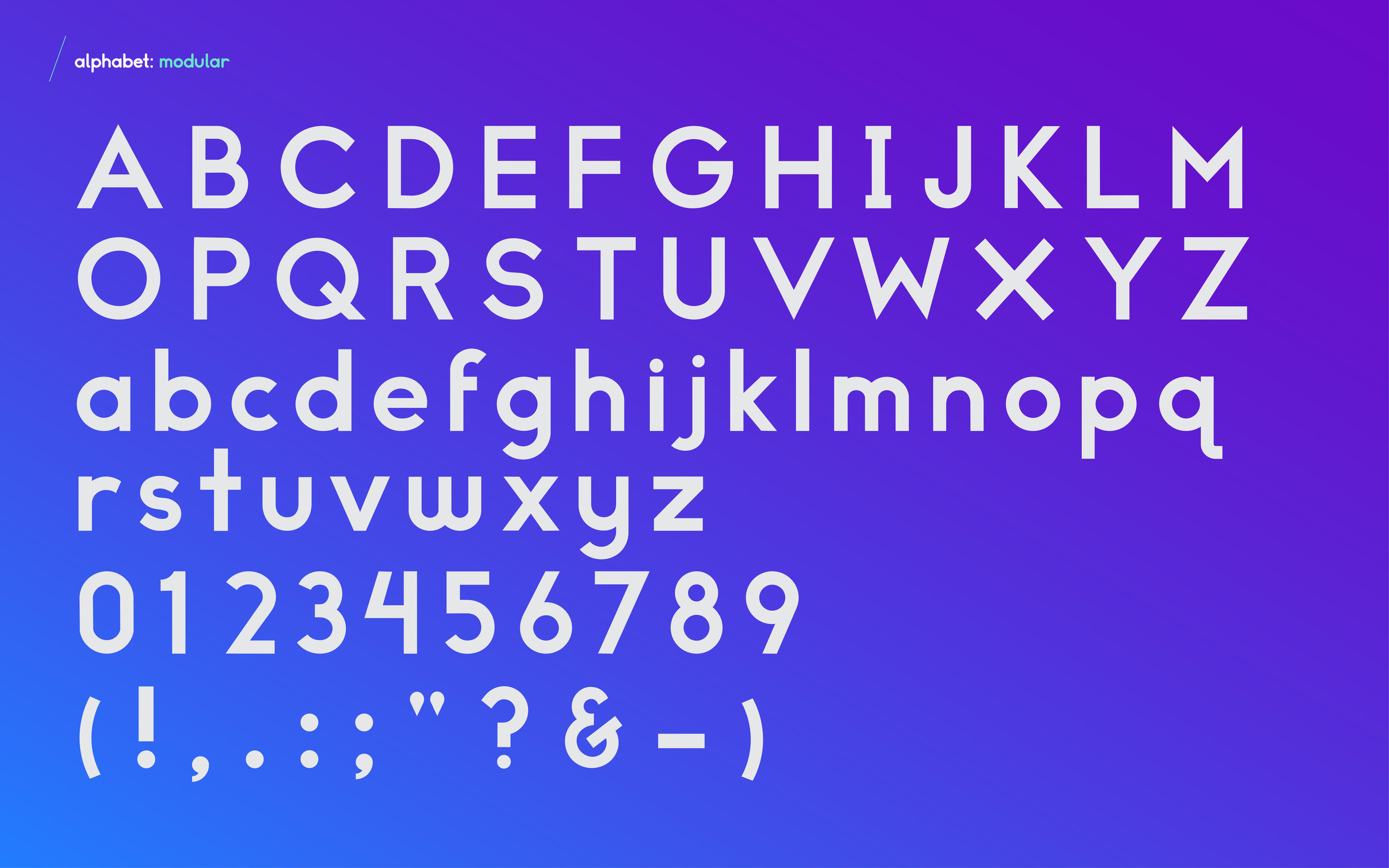
Typographie gratuite : Somatic par Lauren Lee
Typographie / Police d'écriture gratuite (free font) : Somatic par Lauren Lee
La designer et illustratrice américaine Lauren Lee nous propose une création typographique originale en téléchargement gratuit. La typo Somatic est disponible en deux styles différents (rounded et modular). Cette police free est à télécharger en bas de l’article.